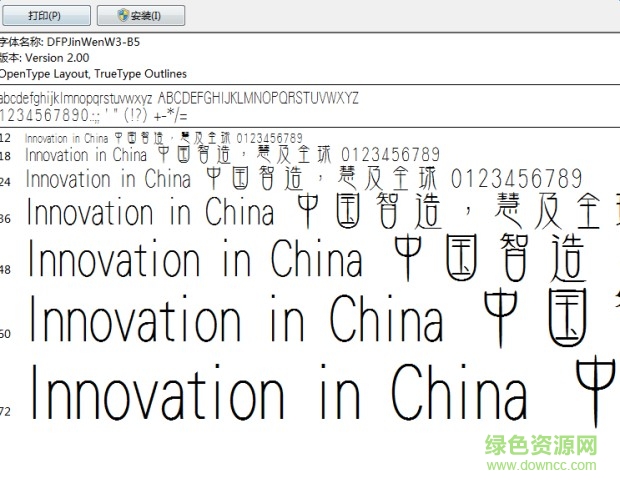
軟件介紹 軟件標(biāo)簽: 華康金文 華康字體 華康金文體ttf字體包收錄了簡(jiǎn)體和繁體字體兩款,該字體直筆多,豐富豐富,弧線過渡流暢,不易識(shí)別,多用于藝術(shù)設(shè)計(jì)或是古書封面,有需要者快來綠色資源網(wǎng)免費(fèi)下載吧!字體的外形特征1.扁體字有左右流動(dòng)的動(dòng)感;2.斜字有向前或向斜流動(dòng)的動(dòng)感;3.長體字有上下流動(dòng)的感覺。華康金文字體安裝方法方法一:直接將字體復(fù)制到C:\WINDOWS\Fonts;方法二:控制面板/字體/文件/安裝新字體;方法三:針對(duì)win7系統(tǒng),用戶只需選中字體右鍵安裝即可。 軟件截圖 上一張下一張(1 / 1) 安裝詳細(xì)截圖 猜你喜歡 繁體字體 繁體字體 繁體字體有哪些?小編今天為大家推薦幾款好看的繁體字體,包含了繁體鋼筆字體、繁體隸書字體、繁體毛筆字體、繁體行楷字體等不同類型的繁體字體!廣告、PPT、海報(bào)、雜志等領(lǐng)域都可使用! 查看更多>> wow魔獸世界臺(tái)服字體包 2.40M/中文/0.0/ttf免費(fèi)版下載 繁體書法字體 3.41M/中文/6.6/下載 楷書繁體字體包 9.76M/中文/8.0/下載 隸書繁體字體 5.46M/中文/4.2/.ttf下載 茶碗古刻繁體 5.37M/中文/5.0/下載 hyx4gf regular 3.41M/中文/8.0/下載 其他版本下載 標(biāo)題 大小 更新日期 下載 下載地址 電腦版 華康金文簡(jiǎn)/繁體字體 點(diǎn)擊報(bào)錯(cuò) 軟件無法下載或下載后無法使用,請(qǐng)點(diǎn)擊報(bào)錯(cuò),謝謝! 關(guān)閉報(bào)錯(cuò)反饋 請(qǐng)描述您所遇到的錯(cuò)誤,我們將盡快予以修正,謝謝! *必填項(xiàng),請(qǐng)輸入內(nèi)容 本類最新 華康漆隸體繁w5 wow魔獸世界華康少女字體ttf 免費(fèi)版 華康蕓風(fēng)體w3 繁體 華康pop2體w9 p 華康粗黑體繁 dfpyuanw7字體 ttf版 用戶評(píng)論 熱門評(píng)論 最新評(píng)論 發(fā)表評(píng)論 查看所有評(píng)論(0) 昵稱: 請(qǐng)不要評(píng)論無意義或臟話,我們所有評(píng)論會(huì)有人工審核. 字?jǐn)?shù): 0/500 (您的評(píng)論需要經(jīng)過審核才能顯示)